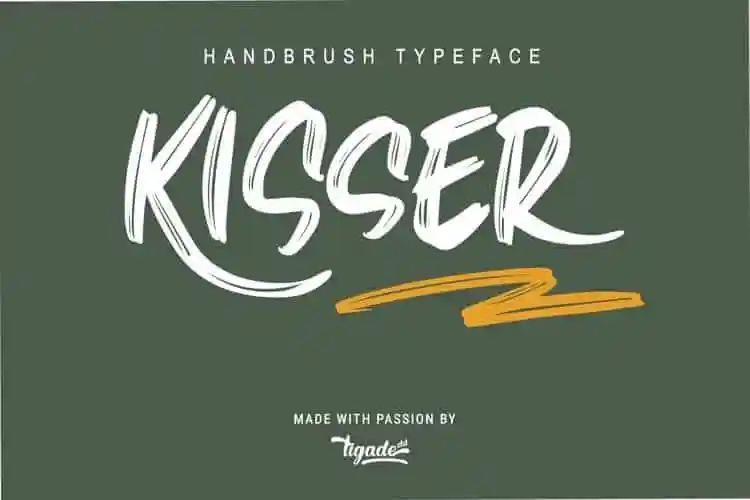
Kisser Brush Font – Download Grátis
A fonte Kisser Brush é uma elegante fólia script, elaborada com mão livre e carregando um ar alegre e pomposo. Criada pelo designer Tigade Std, essa fonte estilosa explode com vitalidade e é perfeita para logos, roupas, frases ou qualquer projeto que necessite de uma forte injeção de estilo tipográfico. Com muita atenção aos detalhes naturais dos traços e às sutilezas finas, Kisser Brush está altamente recomendada. Suas linhas fluidas são atraentes tanto para uso profissional quanto casual, tornando-a perfeita para aplicar em embalagens de produtos, roupas ou qualquer outra campanha visual que busque um toque criativo e sofisticado. Essa fonte é uma ótima opção para quem busca estilizar textos com elegância, modernidade e personalidade. Com Kisser Brush, você pode enriquecer seus projetos com um charme único que vai deixá-los sobressair no mercado de marketing visual.